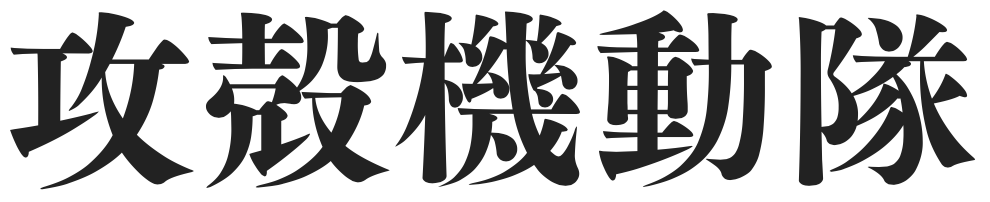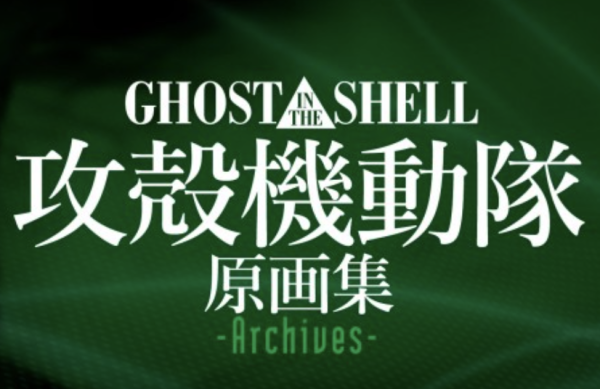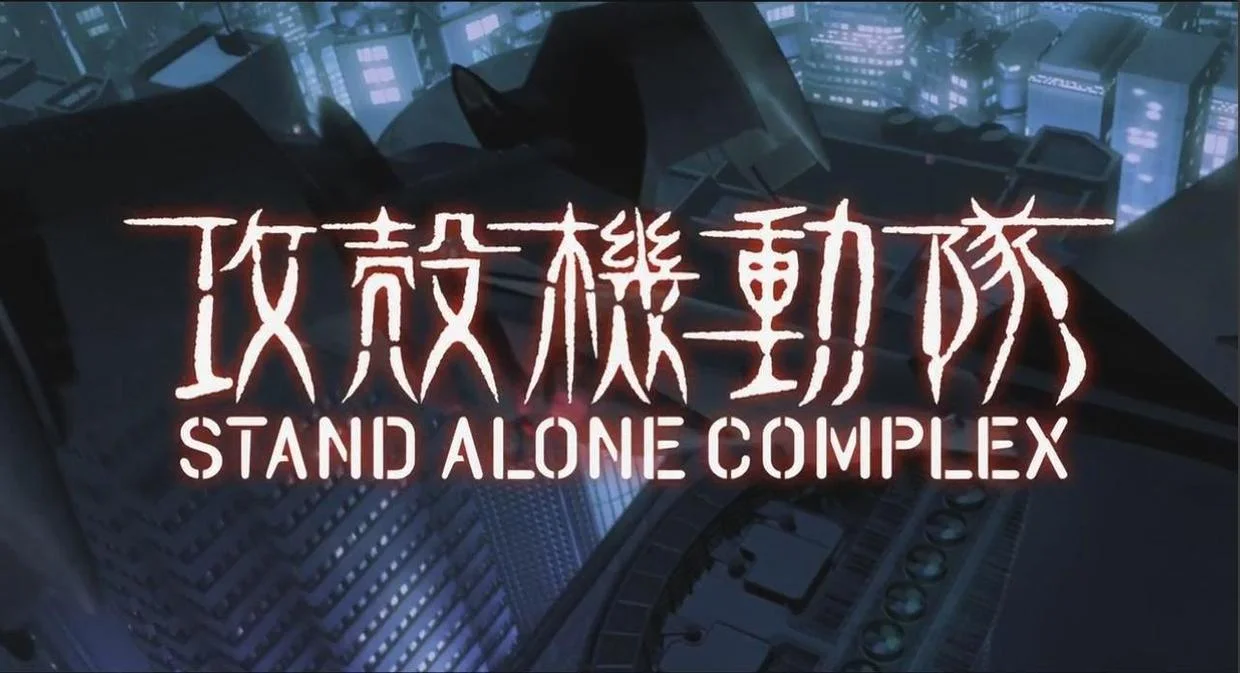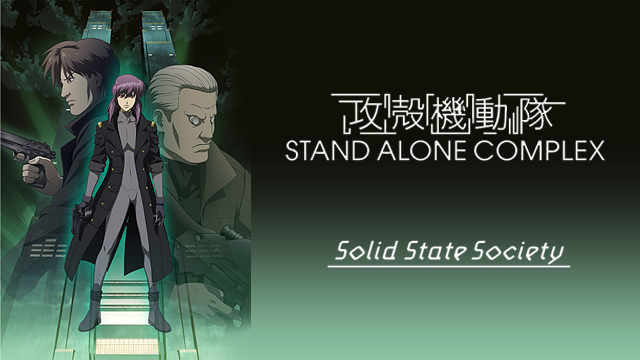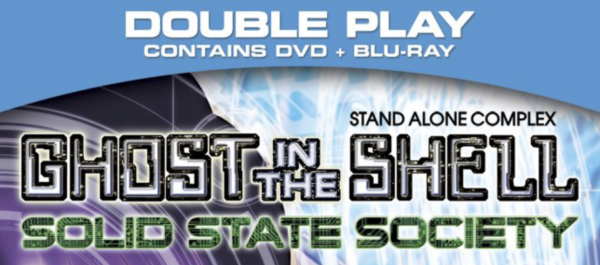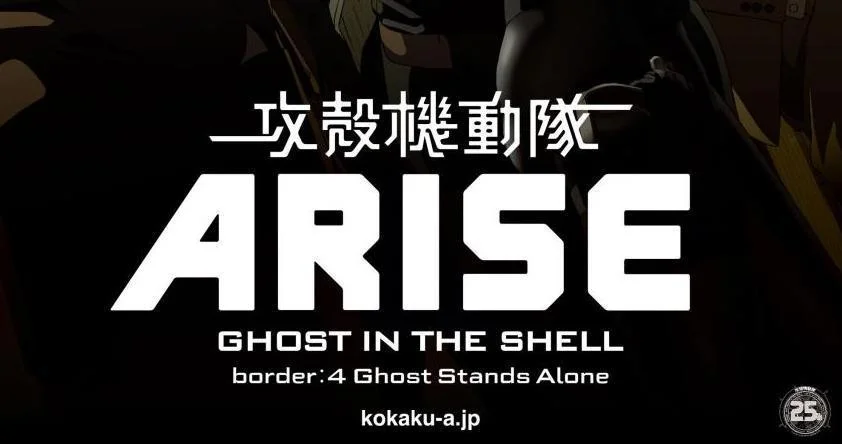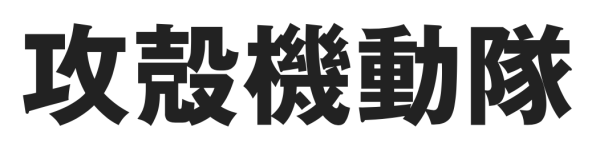
不過這篇文章倒不是影評。作為一個沒有讀過原作漫畫的人,我想粗淺談談的,是動畫(數個 TV 版、OVA 系列及劇場版)與真人版所使用過的幾種標題字體。
《攻殼機動隊》的動畫標題字體,並沒有從開始就定下某個規範,而是經歷了一個變化的過程,在這個過程中,有過幾種字體同時出現的情況。但要說流傳最廣、最具代表性的,想必是從 1995 年押井守執導的第一部劇場版開始使用的中間帶有三角形的主標題 logo。雖然後續作品的海報標題多有變化,但這個 logo 似乎是以「主 logo」的角色,一直在各處出現。
不只是正片,在之後面世的各種周邊產品,例如《GHOST IN THE SHELL/攻殻機動隊 2.0 ORIGINAL SOUNDTRACK》和《GHOST IN THE SHELL / 攻殻機動隊 原畫集 -Archives-》的封面上,這個設計也多被沿用。
從以上四張圖片可以看到,搭配英文「GHOST IN THE SHELL」的日語漢字至少有三種字體。第一張裡的無襯線字體選擇我認為是不恰當的,與英文字體並不搭配。第二、三張的選擇較佳。第二張採用的,我猜,是參與「思源宋體」計畫的 IWATA 旗下的イワタ特太明朝體オールド。海報設計師還在原有字形基礎上,拉長了每個字的「撇」的部分,同時為了追求視覺平衡而縮緊中宮,調節了字形結構。這麼一來有點「清刻本悅宋」的感覺,顯得飄逸靈動,也「酷」了不少。這樣的風格讓我想到藤田重信設計的築紫明朝體的「見出ミン」系列。這是一套帶一點手寫楷體韻味的、俊秀瀟灑的粗宋,同時有刻字和手寫的風格,流動感很強,非常漂亮。
以下是未經調整的イワタ特太明朝體オールド:
以下是未經調整的築紫C見出ミン:
第三張用的,應該是 SCREEN 出品的ヒラギノ明朝。(上面三種日文字體的名稱,姑且分別翻譯成叫「岩田老特粗宋」、「築紫標宋」和「冬青宋體」吧。)
而「GHOST IN THE SHELL」所使用的字體都一樣,應該是由 Linotype 出品、Morris Fuller Benton 在 1911 年設計的襯線體 Bodoni Bold Condensed。設計師在字形已經收窄的基礎上,對排版做了微小調整,進行了一些橫向的擠壓,縮小了 S 和 T、E 和 L 之間的字偶間距,讓標題整體變得更緊湊。以下是未經調整的 Bodoni Bold Condensed:
以下是海報上標題的掃描截圖:
在 2004 年上映的押井守導演的劇場版第二部《Ghost in the Shell 2: Innocence》的海報(下圖)上可以看到,之前「IN THE」外面的三角形被去掉了,字偶間距被進一步調整縮小,但整體設計還是保留了下來。
襯線體可以追溯到古羅馬時期的圖拉真石柱銘文。而這裡使用的 Bodoni 則是一種經典的現代(Didone 或 Modern)風格襯線體。現代風格帶有橫平豎直的幾何特徵,每個字母都像列隊的士兵一樣站得直挺挺的。得益于刻字技術的進步,對比舊風格(Old Style),現代風格一般採用極細的襯線,具有強烈的粗細對比,重心線的傾斜角度也逐漸接近垂直——這是手工書寫向現代排印轉變的一個表現。這種襯線體常被用來表現客觀、高級、銳利、工業、嚴肅而不失優雅等特徵。所以許多時尚奢侈品牌也用現代風格襯線體作為 logo,比如 Giorgio Armani 和 Burberry 就使用了現代風格襯線體的先驅 Didot,而 Valentino 就採用了跟這裡一樣的 Bodoni 字體。
Bodoni 是由義大利人 Gianbattista Bodoni 於 1790 年鑄造的(據說是受到 John Baskerville 的 Baskerville 字體影響)。它被認為是現代風格字體的經典之一,後世有許多複刻、精修和再設計的版本出現。這套字體有幾個字形(glyph)比較有意思,例如它的 M 特別窄,Q 的尾部先垂直向下再轉彎,以及 R 的尾部有個漂亮的弧線等等,只是這些特點在「GHOST IN THE SHELL」這幾個單詞裡沒有出現。
有意思的是,不知出於何種考慮,在1995 年劇場版的國際版英文海報中,標題字體被換成了 Bauer Types 出品的 Bauer Bodoni Bold 和 Bauer Bodoni Bold Condensed 的「修改混合體」。
未經調整的 Bauer Bodoni Bold Condensed 如下:
未經調整的 Bauer Bodoni Bold 如下:
不過,其實無論是哪種 Bodoni,都非常符合《攻殼機動隊》這部探討科技哲學、未來犯罪和人性糾纏的「文藝動畫片」的調性。Bodoni 銳利的尖角和筆直的形態,傳遞出一種冷峻嚴肅的態度。這套字體在當年傳遞出了工業革命之下的時代新風,Production I.G 將它用在《攻殼機動隊》這樣一部帶有反思色彩的作品上,或許可以理解成是某種隱喻?
無獨有偶,同樣是 1995 年面世、亦屬許多人心中科幻神作的《新世紀福音戰士》,在標題字體上也使用了襯線體,但是不像《攻殼機動隊》,他們選擇了 Times New Roman Bold Condensed 這種帶有過渡(Transitional)風格的襯線體。也許這麼做是為了體現「Evangelion」這個詞背後凝重的「時間感」吧。顧名思義,過渡風格是舊風格與現代風格的中間地帶。跟上面的 Bodoni 對比,可以明顯看出字形筆劃和襯線的粗細差異大有不同。
而在 2002 年《攻殼機動隊》TV 版第一季發行時,除了使用上述的 Bodoni 標題,還有如下圖中的另外一套標題字體並行出現。標題中的日文部分,似乎是採用了 DynaFont DF 金文體,並且進行了一些裝飾性的調整。
以下為未經調整的 DF 金文體:
「金文體」是以 1978 年河北省平山縣出土的「中山王方壺」上 448 個字的銘文為原型製作的。日本 DynaFont(臺灣華康字型在日本的分公司)在設計之時,在不破壞神秘感的前提下加入了一些現代化的感覺。在《攻殼機動隊》這樣一出以未來做背景的戲裡用上中國戰國時代風格的文字,明明是高科技,卻搞得像是出土文物一般,大概是為了追求給觀眾帶去強烈的感官對比吧。
而英文部分,則應該是對 Barry Deck 在 CalArts 學生時期設計的 Template Gothic 進行一系列深度修改的結果。以下為未經調整的 Template Gothic Bold:
以下是標題字體:
上下二圖的區別是明顯的,但也可以看出,標題字體裡有許多 Template Gothic Bold 的影子。假若我的猜測正確,那麼刻意不採取現成的軍事風格噴塗字體,卻轉而對現有字體進行大幅改動,這個選擇背後,有著怎麼樣的故事呢?Template Gothic 是以「不完美」而著稱的字體,是「不完美之人類棲居的不完美之世界的不完美之語言(the imperfect language of an imperfect world, inhabited by imperfect beings)」。也許「不完美」這個意象,便是製作方費盡心機想要傳達的?
在 2004 年 TV 版第二季《攻殼機動隊 S.A.C 2nd GIG》,標題中出現了公安九課的數字「9」的變體,標題字體改成了 Matrix II Bold,調整了字偶間距,為數位「2」使用了更大的字型大小,並且對標題裡的字母「S」了些類似 Matrix II Semi Wide 的「加寬」處理。Matrix II 是 Zuzana Licko 在 1986 年對原來基於 bitmap 的 Matrix 字體家族進行重新設計的結果,是首批 PostScript 字體之一——Adobe 在 1985 年才對外公開了 PostScript 這門語言。打這之後,數位字體設計師可以在電腦上用貝茲曲線畫好字形,然後在任意的解析度和尺寸下進行渲染——在之前,可都是要一個個圖元拼起來的。TV 版第「二」季,對應使用 Matrix「II」,不知道是否巧合。順便一提,據說受到《攻殼機動隊》啟發而拍攝的《駭客帝國》系列,英文片名也是「The Matrix」。
以下是未經調整的 Matrix II Bold:
以下是未經調整的 Matrix II Semi Wide:
另外可以看到,日文標題部分的字體也做了調整,但乏善可陳,按下不表。
2006 年,神山健治又作為導演推出了劇場版 OVA《攻殼機動隊 S.A.C SSS》(並且在 2011 年出了 3D 重製版)。從標題字體來看,這是「全面無襯線化」的開始。日語標題使用了類似中文等線體的字體,樸素端正,十分清晰,但也許是嫌過於單調了,又加了一些(有點莫名其妙的)裝飾性元素,大概是想體現未來都市的天際線?「STAND ALONE COMPLEX」使用的是與著名的 ITC Avant Garde Gothic 相似的 URW Gothic 字體,風格上屬於幾何(Geometric)無襯線體,與等線體在視覺上倒是很搭配。
以下是未經調整的 URW Gothic:
比較有意思的是「Solid State Society」的部分,使用了與 Matrix II 一樣,同為 Zuzana Licko 設計的 Lunatix 字體,並且將其手動傾斜(slope)了(這套字沒有 Italic 版本)。「Lunatix」跟「lunatics」同音,也就是「精神異常者、狂人」的複數形式——而這部劇場版裡的確有許多瘋狂癡癲的情節。上面的日文等線體和英文幾何無襯線體都是清晰,理性、簡潔,沒有手工感,並且非常冷靜的字體。而隨著視線往下移動,瞬間轉換成仿佛是歪咧著嘴在瘋笑的 Lunatix,這可以說是通過字體在講故事了。
以下是未經調整的 Lunatix:
與此同時,這部 OVA 的藍光碟封面設計就比較糟糕了。在這截圖的方寸之地就出現了三種風格五種字體搭配三種特效,令人眼花繚亂。我猜這位平面設計師的年齡應該比較大,所以會為「GHOST」和「SHELL」兩個單詞選擇用類似 Bob Newman 設計的「Data 70」這樣的字體來體現「科技感」和「未來感」——這思路在上世紀 90 年代也許還行得通,但這樣的設計放在 2006 年,就有點「落伍」的感覺了。
在《攻殼機動隊 S.A.C SSS》之後,接下來登場的是 2013 年到 2014 年期間推出的四部劇場版《攻殼機動隊 ARISE》系列,由黃瀨和哉擔綱總導演一職,在電視放送時的標題叫《攻殼機動隊 ARISE ALTERNATIVE ARCHITECTURE》。下圖海報標題裡日文「攻殼機動隊」和英文「ARISE」使用的字體應該是基於某種(我看不出來的)美術字體深度修改而成的。而「GHOST IN THE SHELL」和下面的每部之名稱,使用的則是 Bank Gothic 字體的 medium 和 light 兩種字重版本。
以下是未經調整的 Bank Gothic Medium:
電影海報或者遊戲封面的副標題,經常會用 Bank Gothic 來寫(在上面「S.A.C 2nd GIG」那張圖裡,右上角的「VOL 06」也是用了 Bank Gothic)。但在這裡採取這個字體,除了「跟主標題字體比較搭配」之外,或許暗含有向前作致敬的意味——Bank Gothic 的設計者與 Bodoni Bold Condensed 一樣,都是 Morris Fuller Benton——當然更可能是我想多了。從十幾年前強調「不完美」的 Template Gothic,到整齊穩重的典型「都市標牌字體」Bank Gothic,時代審美在變,《攻殼機動隊》的導演、敘事方式和內容也隨之不同。打個奇怪的比方,從大改 Template Gothic 到直接使用 Bank Gothic,仿佛一個喜歡動腦筋鼓搗改裝車的暴走青年,十幾二十年後變成了四平八穩地開著富豪送孩子上學去的中年大叔。雖然孰高孰低見仁見智,但總歸讓人不禁有點唏噓。
2015 年,依然是黃瀨和哉執導,《攻殼機動隊 新劇場版》上映。這是《攻殼機動隊》漫畫誕生 25 周年的紀念作品。
標題的日文部分在某種中宮比較小的粗黑體上進行了不少「噴塗式字體」風格的修改。我推測元字體是森澤出品的ゴシックMB101 B。英文「GHOST IN THE SHELL」部分則使用了放大字偶間距的 Linotype Ordinar。
以下是未經調整的ゴシックMB101 B:
以下是未經調整的 Linotype Ordinar Regular:
最後……終於說到了真人版。真人版的標題延續了之前幾作使用無襯線字體的做法,但是恢復了最早的「IN THE 三角形」設計,應該算是在致敬 1995 年的劇場版第一部。在不同的地區和管道,宣傳品上的字體使用有所不同。
英文版海報使用的都是無襯線的 Futura 字體。
雖然現在無襯線體常常被用來表達「科技感」,但要論在歷史上出現的時間,其實無襯線體要早於襯線體。無襯線體可以大致分成四類:早期無襯線(Grotesk)體、新無襯線(Neo-Grotesk)體、幾何(Geometric)無襯線體和人文(Humanist)無襯線體。
而 Futura 則是幾何無襯線體的典型代表。所謂「幾何」,就是強調字形的幾何形狀,使用寥寥數種幾何圖形(圓形、矩形、三角形)等等表現出字母的樣子。
為了增加可讀性和易認性,Futura 字體的頂角和底角非常銳利(同時也跟「IN THE 三角形」這個元素很搭配),小寫字母的升部降部偏長,許多字形都做了近乎正圓的處理。在「GHOST IN THE SHELL」這幾個單詞裡,我們可以看到貌似正圓的「O」。只有當與真正的幾何正圓對比時,我們才會發現 Futura 的 O 的形狀是經過調整的,水準方向的筆劃被微調修細了一些。
第一張圖裡的標題字體,是直接用的 Futura Book。第二張,則應該是在 Futura Medium 的基礎上自行「增肥加粗」增加字重的成果——至於為什麼不直接使用 Futura 家族裡的 bold 或者 heavy 版本,我猜也許是為了尋求與 Futura Book 在字形上的統一。
以下是未經調整的 Futura Book:
以下是未經調整的 Futura Medium:
以下是未經調整的 Futura Bold:
以下是未經調整的 Futura Heavy:
對比可見,bold 和 heavy 版本的字形在形狀上與 Futura Book 有明顯不同。所以或許可以推論,Futura Book 標題字體先於第二種較粗的標題字體出現,所以後者要去努力「配合」前者給人留下的印象。
跟大名鼎鼎的 Helvetica 字體一樣,Paul Renner 在設計 Futura 時,也受到了包豪斯學派「形式追隨功能」思想的影響,強調理性和字體功能——設計師 Chris Daniels 曾經以 Futura 字體設計了一系列關於 Futura 歷史的海報,大標題就是「高效與進步」(Efficiency & Forwardness)。另外,Futura 這個詞在拉丁語裡是「未來」的意思。總的來說,Futura 倒的確是非常適合科幻片。
而也許是為了符合「好萊塢引進片」的頭銜,在日文版的海報和網站上,破天荒地第一次沒用漢字,而是用黑體的片假名拼寫出了「GHOST IN THE SHELL」,也加了跟《攻殼機動隊 新劇場版》一樣的「噴塗」效果。英文標題部分沒用 Futura,倒是選擇了老朋友 Bank Gothic,不過只用了 light 一種字重。
以下是未經調整的 Bank Gothic Light:
簡體中文的海報上是沒有英文「GHOST IN THE SHELL」的,除去化用了三角形這個設計項目和同樣使用黑體之外,標題字體方面可談之處不多。